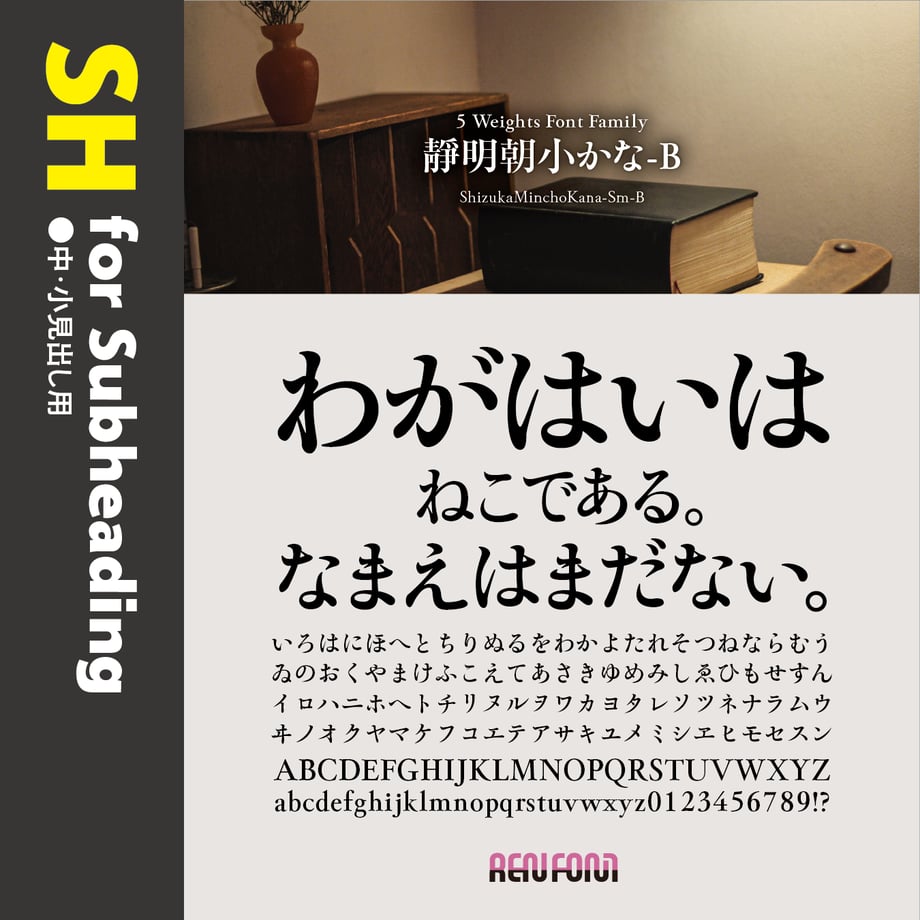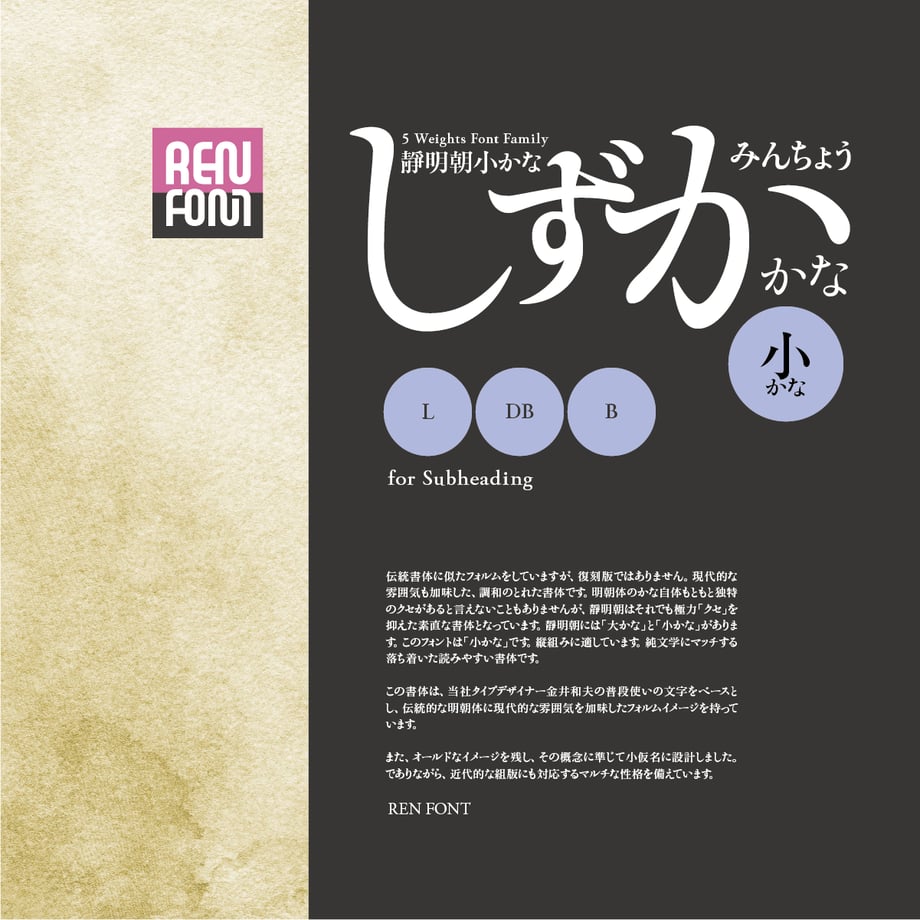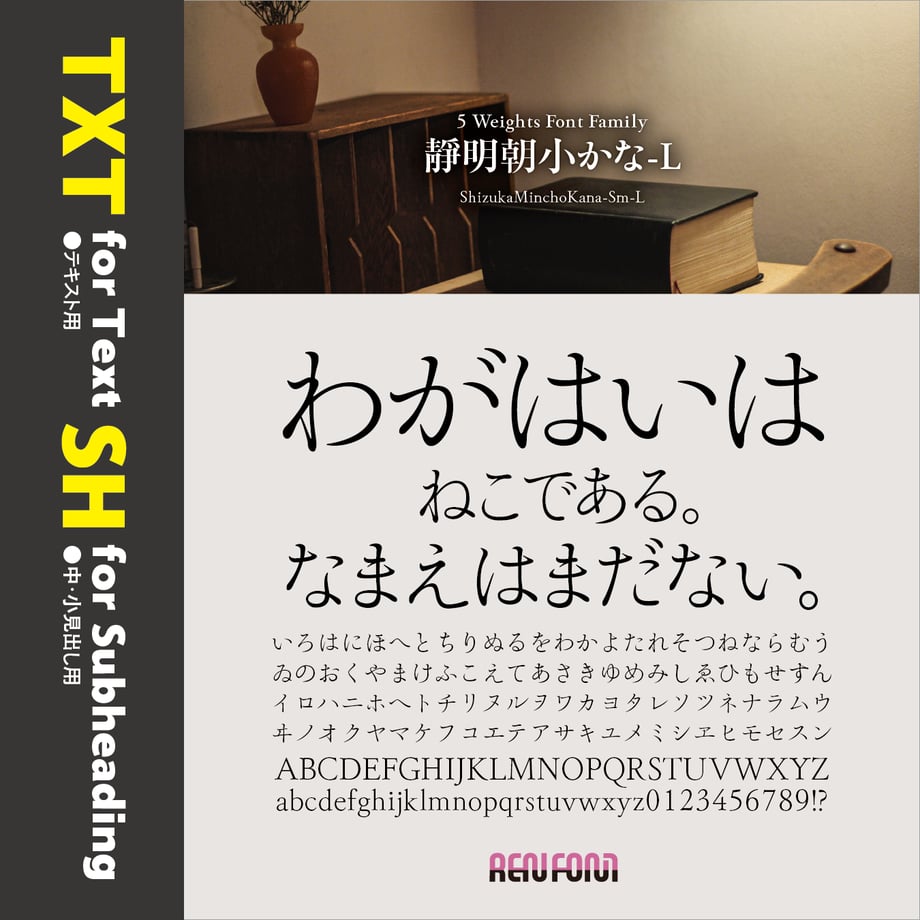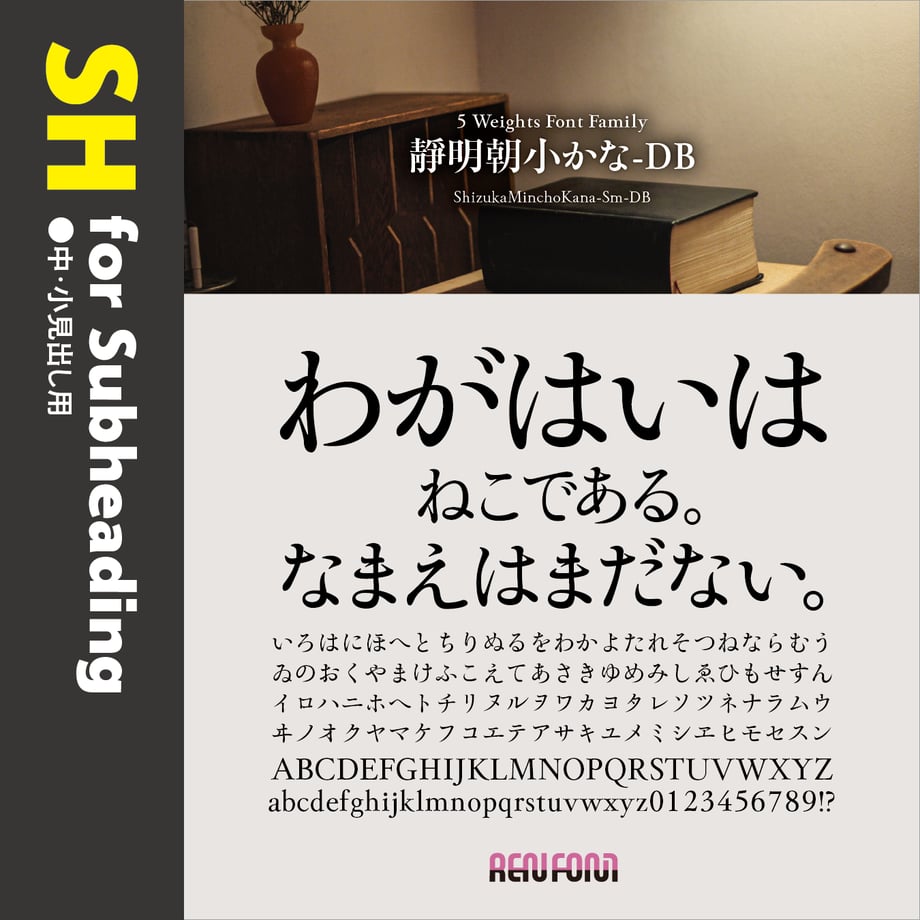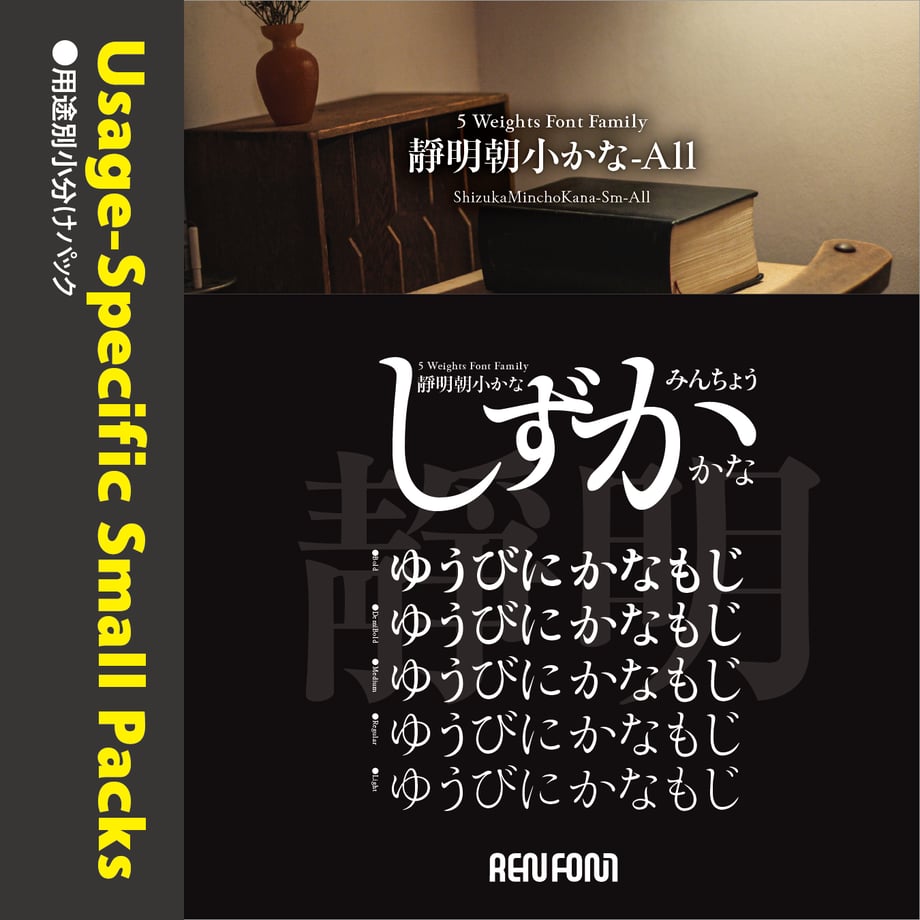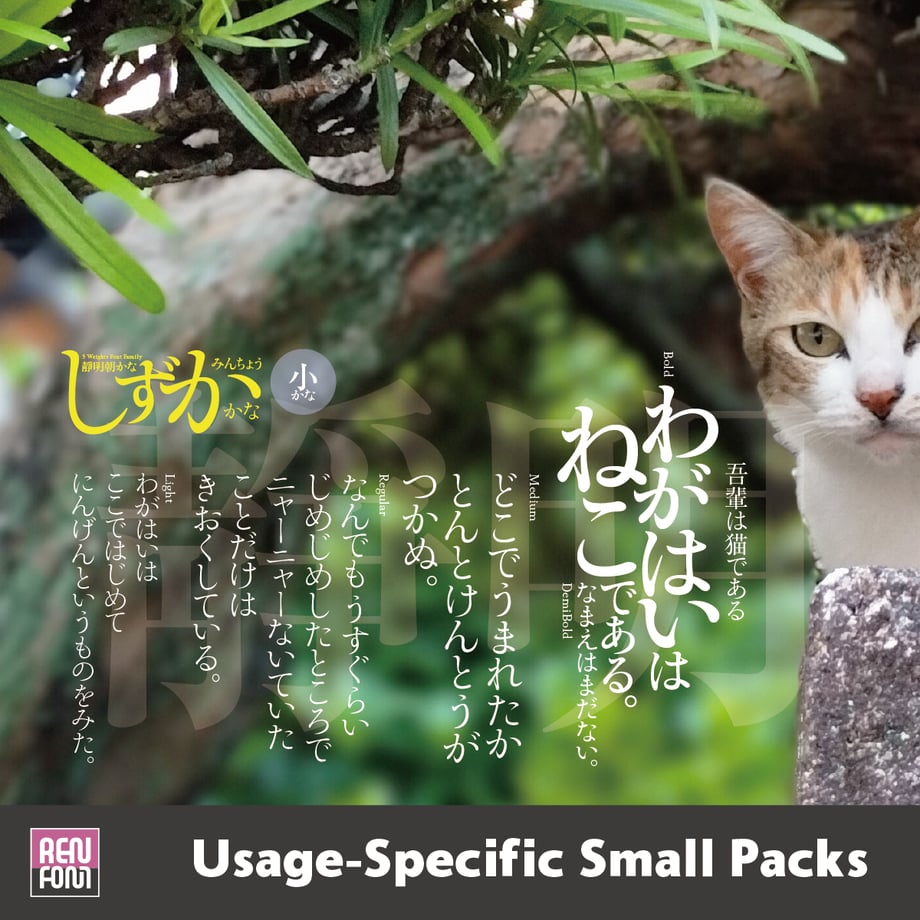
靜明朝小かな-SH(中・小見出し用)L/DB/B
読みやすさにこだわった
靜明朝小かな 5ウェイトファミリー / OpenType
小説などの長文に適した素直なフォルム
伝統書体に似たフォルムをしていますが、復刻版ではありません。現代的な雰囲気も加味した、調和のとれた書体です。明朝体のかな自体もともと独特のクセがあると言えないこともありませんが、靜明朝はそれでも極力「クセ」を抑えた素直な書体となっています。靜明朝には「大かな」と「小かな」があります。このフォントは「小かな」です。縦組みに適しています。純文学にマッチする落ち着いた読みやすい書体です。
この書体は、当社タイプデザイナー金井和夫の普段使いの文字をベースとし、伝統的な明朝体に現代的な雰囲気を加味したフォルムイメージを持っています。「L(ライト)」、「R(レギュラー)」、「M(ミディアム)」、「DB(デミボールド)」、「B(ボールド)」の、合計5ウェイトで構成されています。
また、オールドなイメージを残し、その概念に準じて小仮名に設計しました。それでいながら、近代的な組版にも対応するマルチな性格を備えています。
縦組みに適している理由とは
現代は、すっかり横組みの文化。さすがに新聞はまだ縦組みですが、それ以外では小説などの単行本でしか目にしなくなりました。しかし、かなは本来縦組みに適した作りになっています。それを横組みすると、さまざま問題がおきます。横幅が狭い文字種が多いからです。ベタ組みすると文字間が広く開いてしまう箇所が多くなり、大変読みにくくなります。私たちは実は「習慣」のもとに、普段から読みにくい文章を読まされているのです。
靜明朝小かなは、全体を小さめに設計しました。縦組みには小かなが適しています。一番大きい漢字、ひとまわり小さいひらがな、そして、一番小さなカタカナが混在することにより心地よいリズムが生まれ、読みやすく長時間読んでも疲れないようになっています。
他社「総合書体」との「共存」
現在、世の中に出回っているフォントの数はすでに数え切れないほどになっています。明朝体に限ってもまた然り。
靜明朝かなは5ウェイトありますが、それぞれの太さにさほどの差がありません。本来は3ウェイト展開にすべきかも知れませんが、あえて5ウェイトにしたのにはそれなりの理由があります。
かなフォントは、単独ではさほど存在意義はありません。漢字と組み合わせてはじめて「意味」があります。
フォントのウェイト呼称は、ほとんどのベンダが「ライト」から「ウルトラ」に至る7から9ウェイト展開をしています。ただ、それぞれの太さに明確な基準はなく、各ベンダの判断によります。ですので、例えば「ライト」でも太さが微妙に異なってきます。かなフォントがそれに対応するには、細かいウェイト展開が必要となります。
当社かなフォントの細かいウェイト展開は、それが理由です。お好みに合わせて合成フォントをお楽しみいただければ幸いです。
日本語文章の約70%はひらがな、カタカナが占めているといわれます。それだけに紙面の雰囲気を左右し、決定づける重要なアイテムです。図は、モリサワのリュウミンと靜明朝を並べて比較したもの。同じ文字種でもこれだけ印象が違います。
靜明朝小かなは、長文を組むために開発、読みやすさを重視しクセを極力なくしたフォルムになっており、特に縦組みに適しています。そのフォルムは、のびやかでなめらか。先端は全て丸く処理しました。収筆はすべて跳ねずに止めてあります。また、「か・な・ね」などの収筆は跳ねずに止めてあります。一文字ひともじの独立性を大切にしました。
伝統書体を踏襲したフォルムですが、復刻版ではなく、現代にマッチするシャープな雰囲気も同時に持たせてました。
欧文・数字は、奔放な両かなとは異なり、クセの少ない伝統的なイメージにデザインしました。わずかに「K」「Q」「R」のテールに「かな」の雰囲気を持たせてあります。
格調高いGaramond調の形状ですが、若干現代風な設計になっています。欧文書体としての単独使用にも十分に耐えうる、和文付嘱書体としては稀な、非常に高い完成度を持っています。